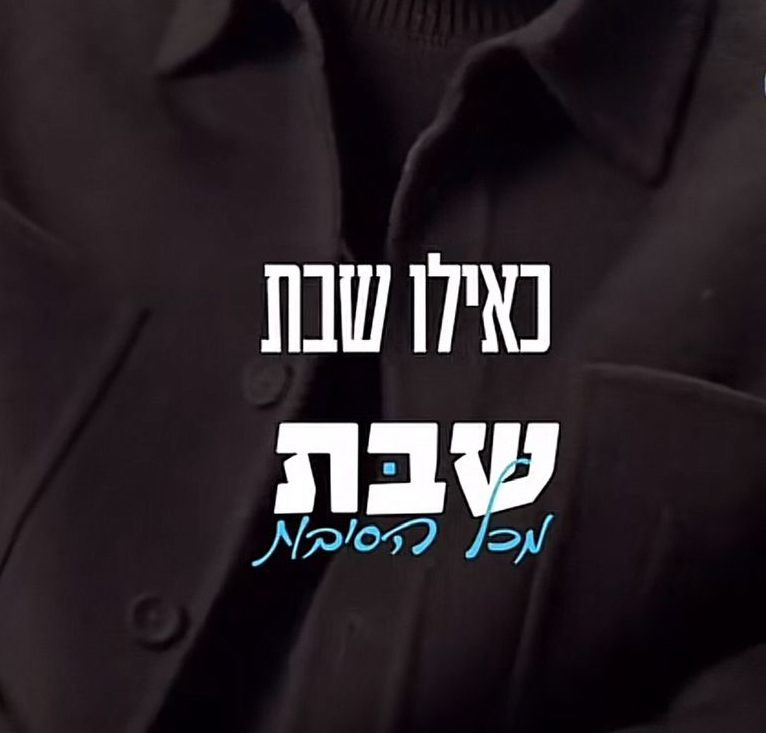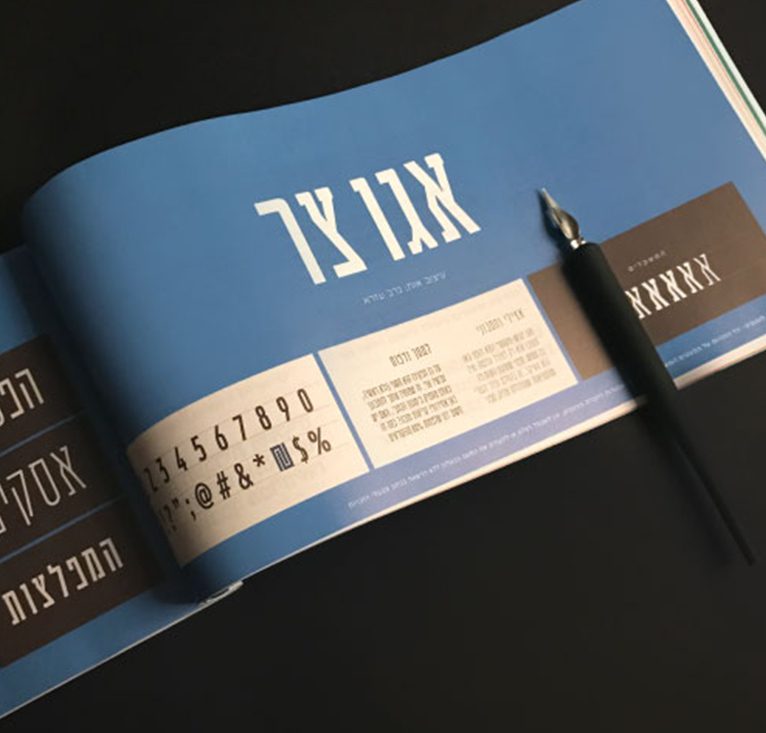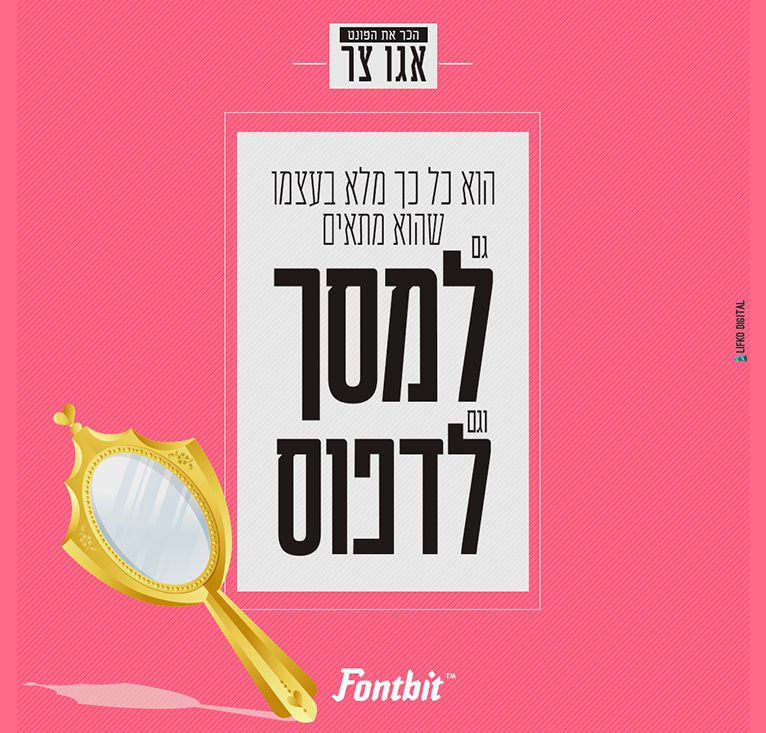
טיפוס האות אגו צר הוא נגזרת סאן סריפית של האות ״אגו סלאב״ שהותאם ויועד לשימוש בכותרות. טיפוס אות בעל מבנה מאורך ואצילי לשלד האלפבית הקלאסי ובעל קו גרפי פשוט ומובהק. ביקשתי ליצור טיפוס אות גרפי חדש לכותרות עיתון שיביא משהו מהארומה של עימוד אותיות הטקסט - פרנקריהל. בזכות הקרבה למבנה הקלאסי התקבל טיפוס אות נח במיוחד לשימוש בעל טקסטורה אחידה ומקצב מובהק. אות ששומרת על רמת קריאות טובה למרות המבנה הצר. טיפוס האות אגו צר הוא נגזרת סאן סריפית של האות ״אגו סלאב״ שהותאם ויועד לשימוש בכותרות. טיפוס אות בעל מבנה מאורך ואצילי לשלד האלפבית הקלאסי ובעל קו גרפי פשוט ומובהק. ביקשתי ליצור טיפוס אות גרפי חדש לכותרות עיתון שיביא משהו מהארומה של עימוד אותיות הטקסט - פרנקריהל. בזכות הקרבה למבנה הקלאסי התקבל טיפוס אות נח במיוחד לשימוש בעל טקסטורה אחידה ומקצב מובהק. אות ששומרת על רמת קריאות טובה למרות המבנה הצר.